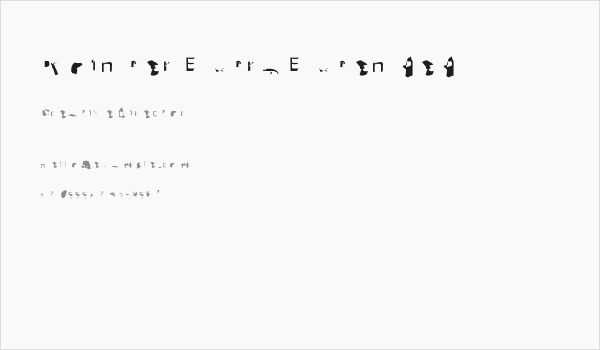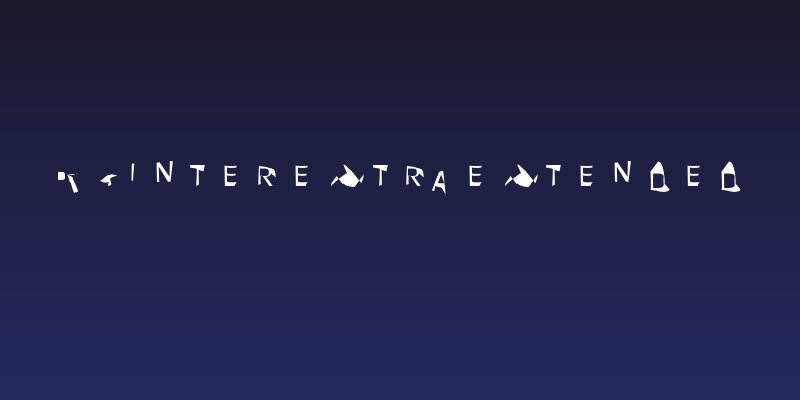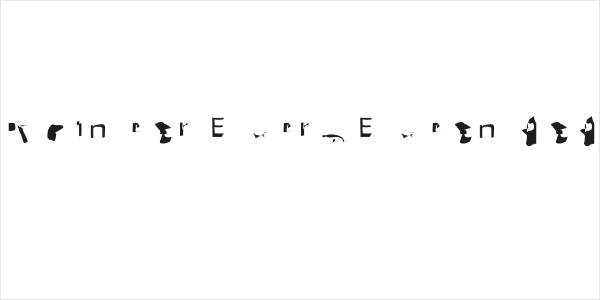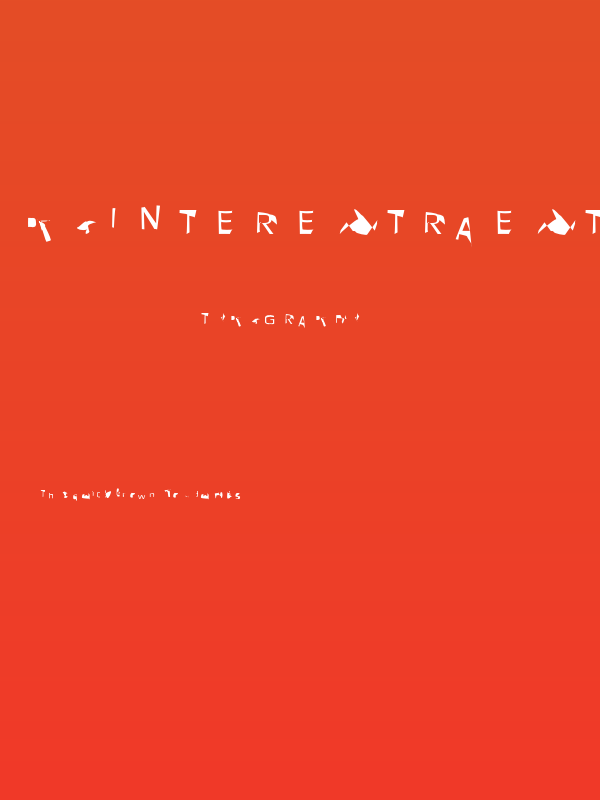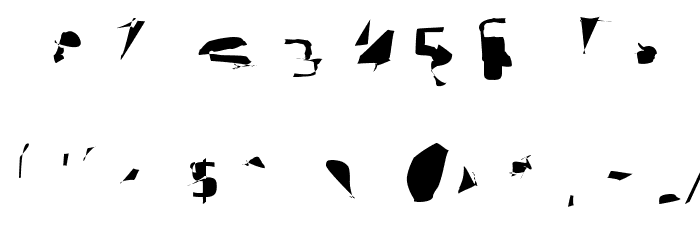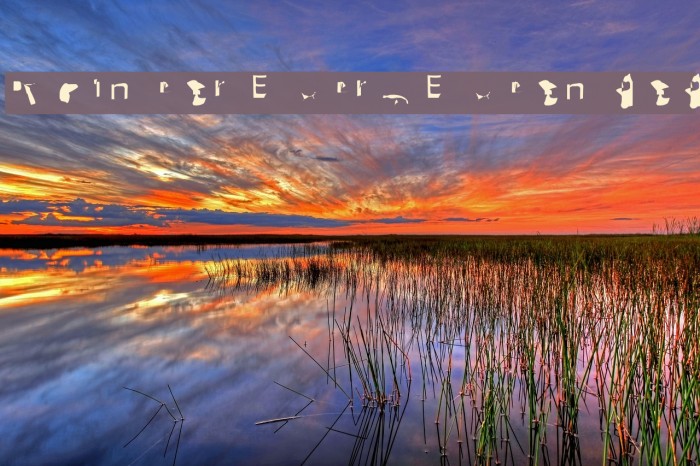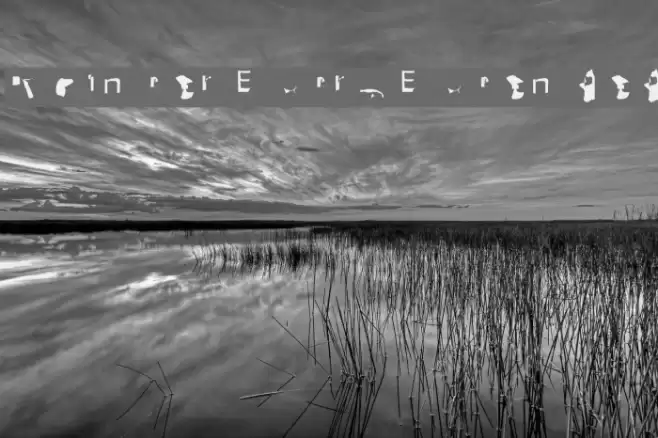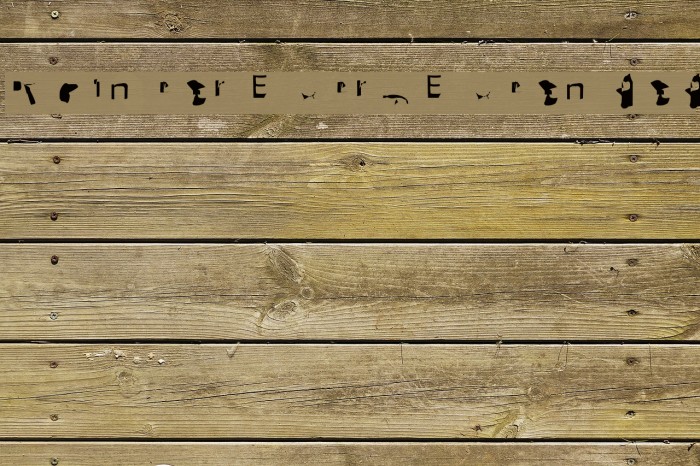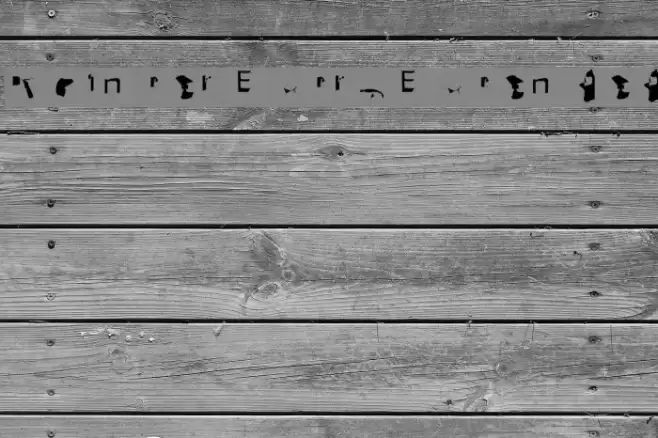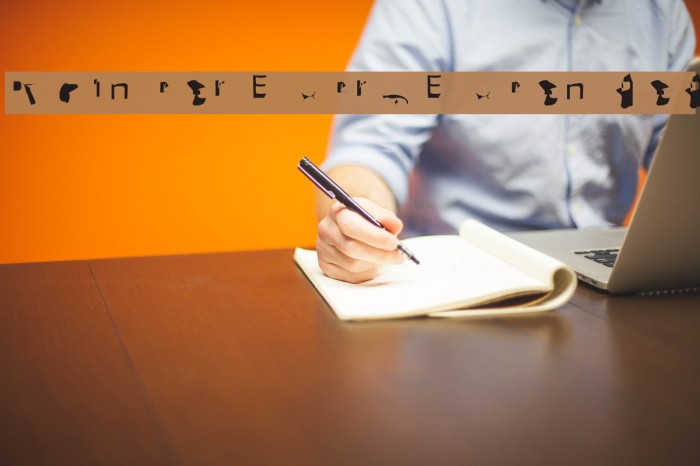
Pointer ExtraExtended Font
✎ Distorted Eroded
| Категория | Distorted Eroded |
| Ширина | Expanded |
| Рекомендуемые проекты | Ideal for avant-garde posters, album covers, or any project seeking a disruptive and innovative visual impact. |